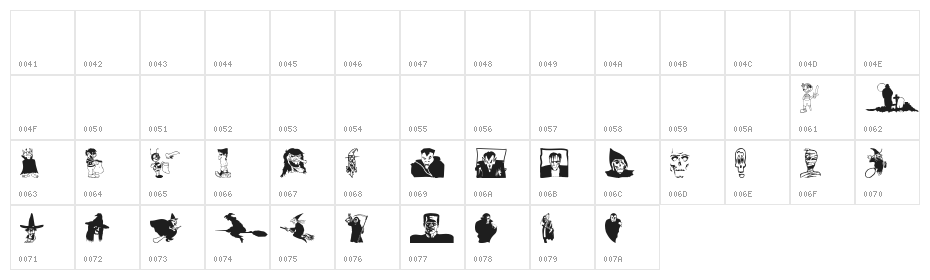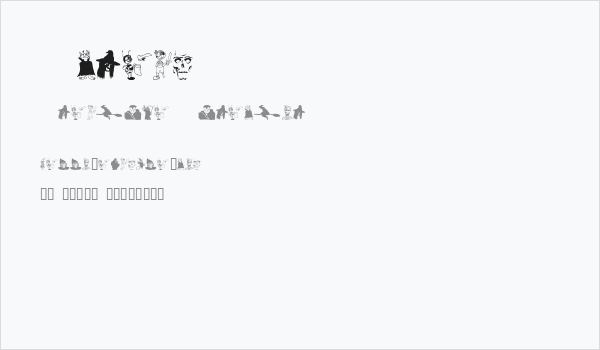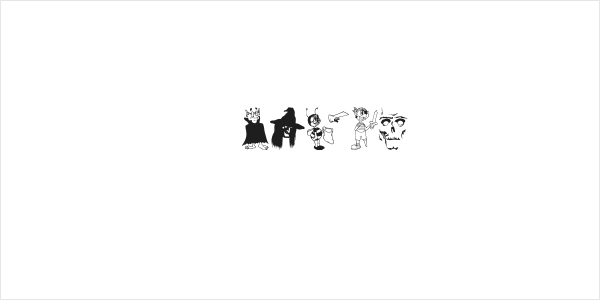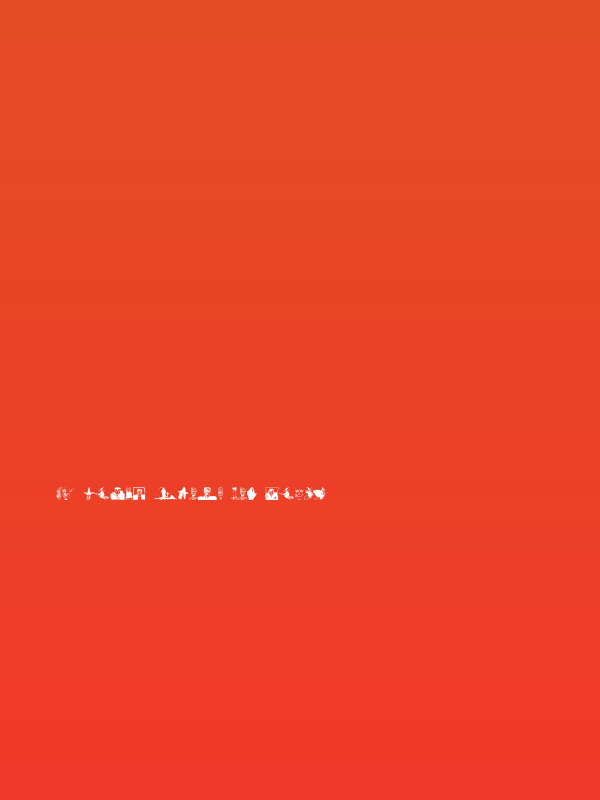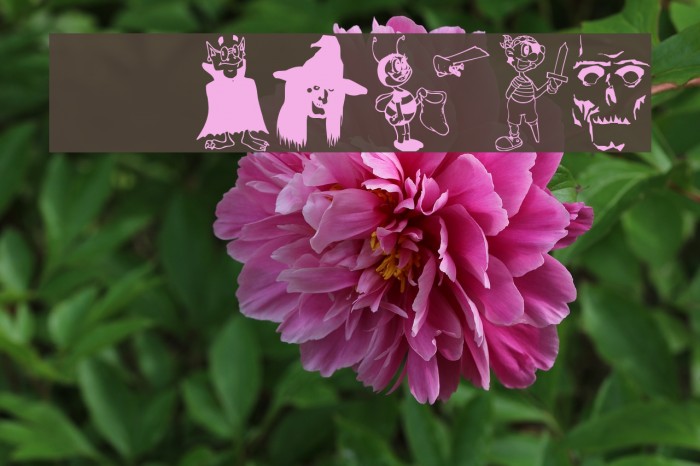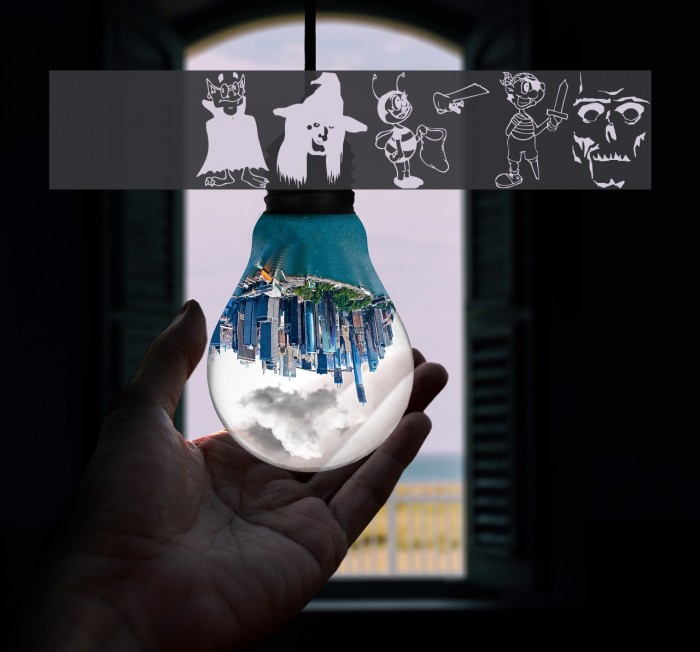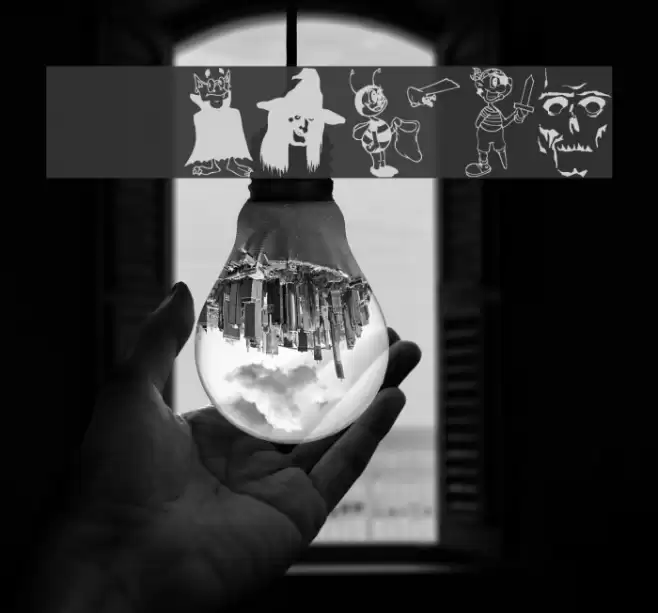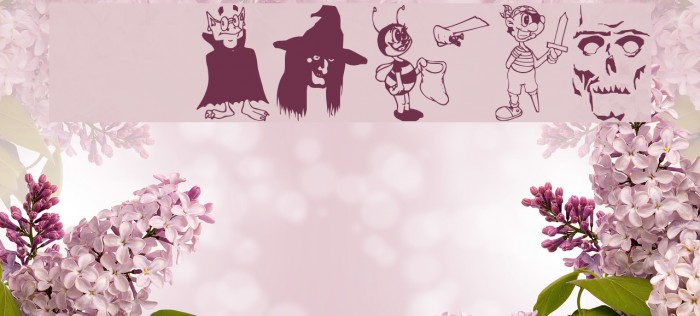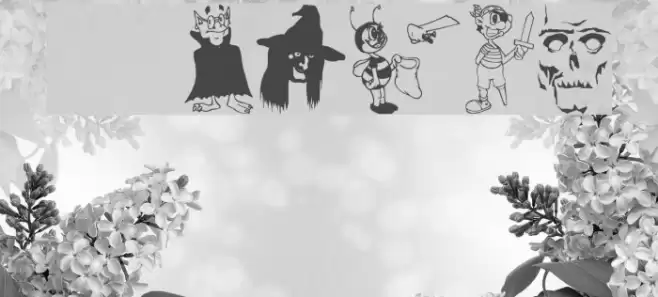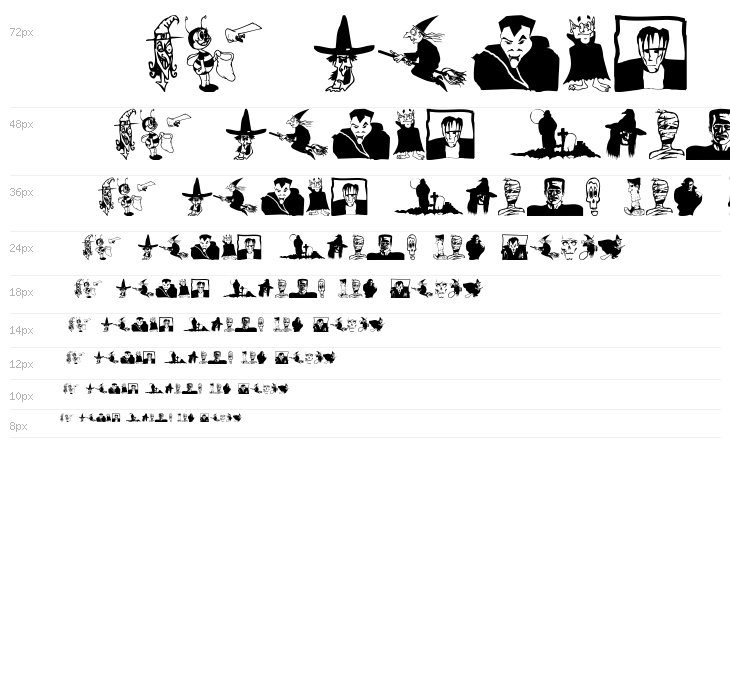
Scream Font
✎ Decorative
| Категория | Decorative |
| Область применения | Logos, Posters, Invitations |
| Рекомендуемые проекты | Ideal for Halloween party invitations, themed posters, or any project requiring a spooky, playful touch. |
Scream